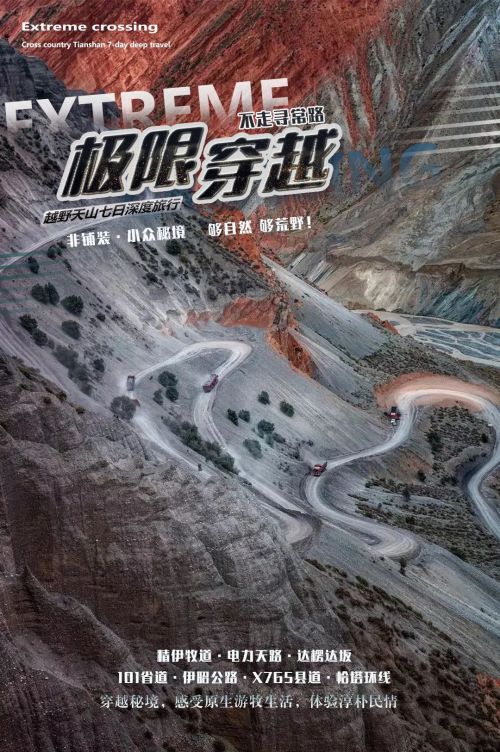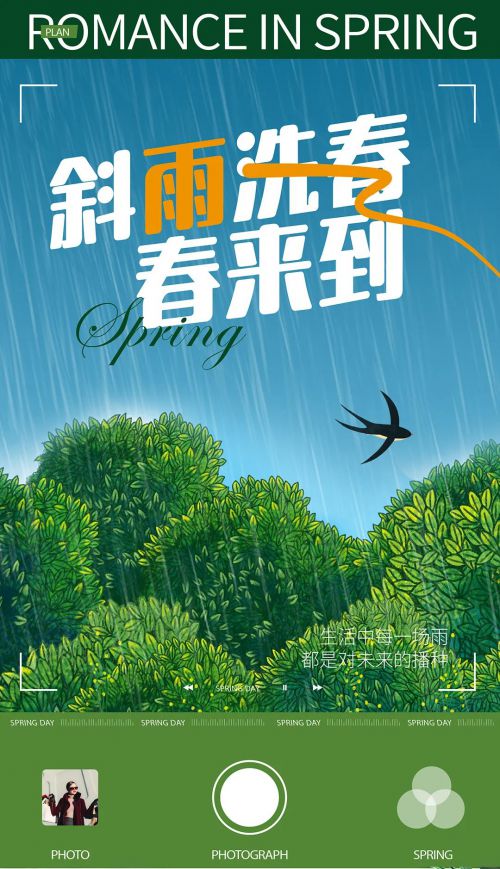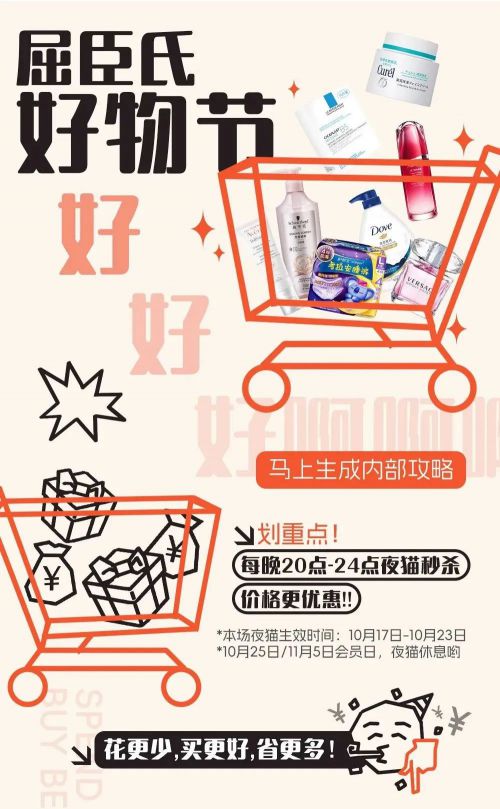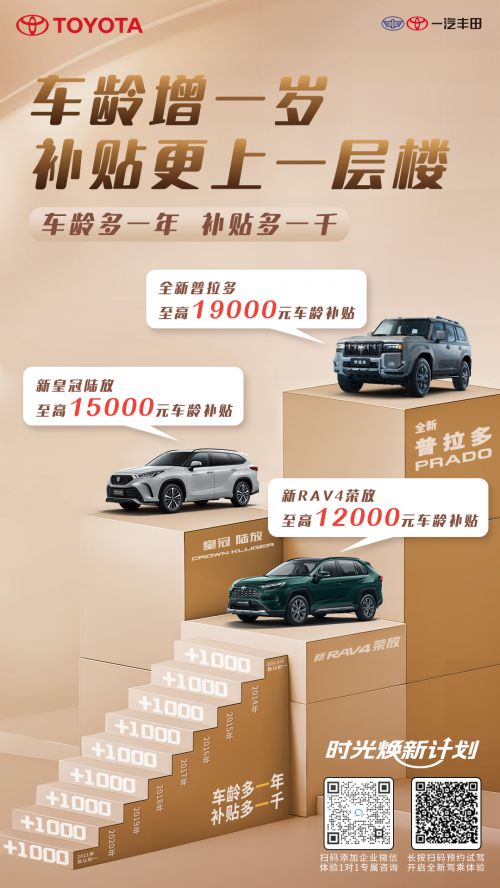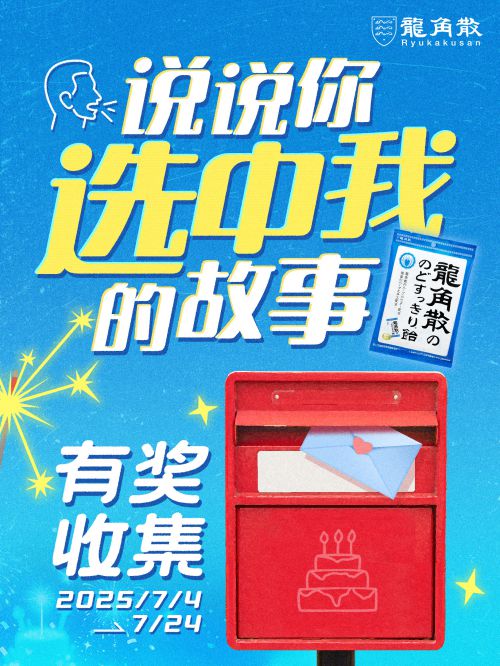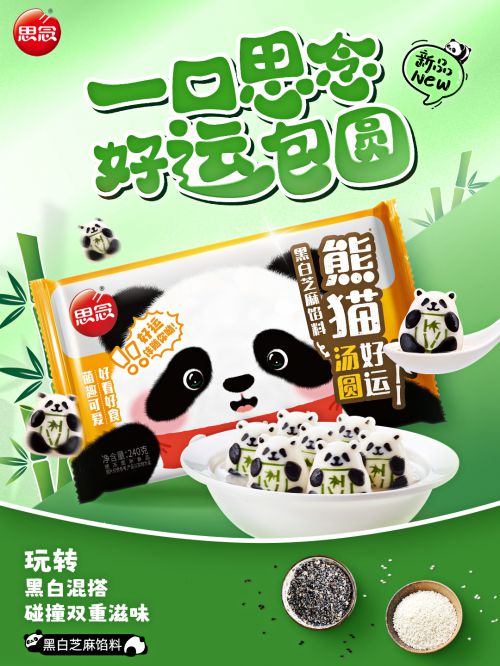
点字朗润体
点字朗润体是点字库推出的创意字体/圆体,以温和亲切的气质融合现代感与端庄优雅,字重饱满粗壮,兼具视觉张力与舒适质感,是会员商用场景中的理想选择。作为创意圆体代表,其设计在传统圆体基础上突破创新,既保留圆润柔和的基底,又以方正结构注入稳重感,形成独特的“刚柔并济”风格。 点字朗润体字形方正规整,重心居中平衡,中宫适中的设计让字符排布整齐有序,既避免松散也不显局促;笔画粗细均匀一致,方头收尾利落干脆,配合断开式的笔画连接,在规整中透出灵动呼吸感,打破沉闷,更添设计巧思。 点字朗润体在笔型细节上暗藏温度,直角线条勾勒出利落框架,笔画末端的精致装饰元素(如圆点般的小巧处理)则注入灵动亲和感,让方正结构与圆润细节形成巧妙对比,彰显“温润亲切”的核心气质。无论是杂志标题的视觉突出、品牌广告的情感传递,还是产品包装的质感提升,点字朗润体都能以粗壮字重强化焦点,以灵动细节传递温度,为设计作品赋予个性与亲和力兼具的文字表达。
卢鑫亚
90后字体设计师,曾获第二届字体之星评委奖,最具商业潜力奖,第三届字体之星评委奖。